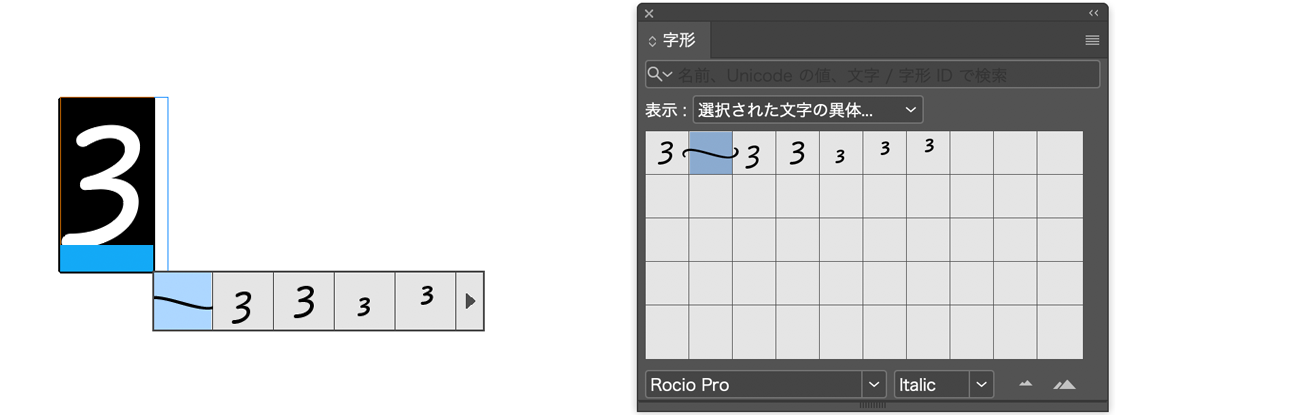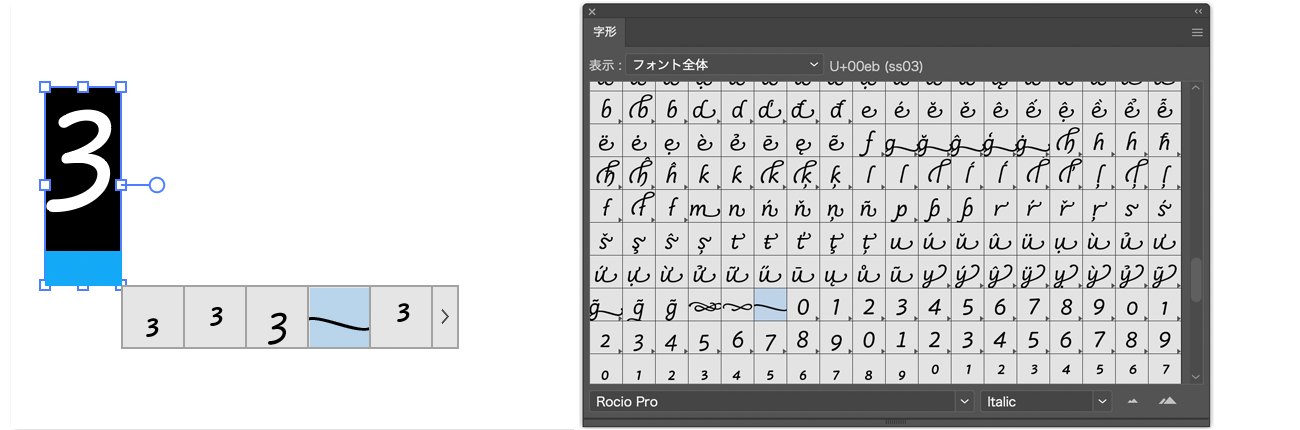
【Rocio Proの特徴】
Rocio ProはRocio(フォントメニュー名:MO Rocio Regular / MO Rocio Italic)を元に文字セットの拡張、ファミリー化、スワッシュ字形へのアクセスの改善をおこなったフォントファミリーです。
各ウエイトのイタリックには装飾的なスワッシュ字形なども多数用意されており、OpenType機能を用いることでテキストの並びに応じた華やかな字形を呼び出して表情豊かなデザインを作り上げることができます。
【Rocio ProとRocioの違い】
Rocio ProはRocioを元に文字セットの拡張とファミリー化を行っているため、スタイル展開や搭載しているグリフの種類が大きく異なります。
ファミリー化に伴いRegularおよびItalicのデザインを調整したため、RocioとRocio Proではデザインも細部で異なります。
また、Rocioでは文脈を判断してスワッシュ字形を呼び出すことがInDesignでのみ可能だった一方、Rocio ProではAdobe Illustratorでも同様のことが可能となりました。
なお、RocioとRocio Proでは文脈を判断してのスワッシュ字形の呼び出しパターンが異なるため、同様の文字列でも必ずしも同様の字形が呼び出されるわけではありません。
このように、デザイン、文字セット、スタイル展開、OpenType機能と多くの面でRocioとRocio Proは異なり、互換性がありません。
そのため、両者間での置き換えを行う場合は組版の崩れにご注意ください。
【Rocio Proの機能と使い方について】
Rocio Proは以下のような機能を備えています。
(1)スワッシュ字形
グリフの並びに応じてスワッシュ字形を呼び出します。文脈を考慮して自動で適切な形を呼び出すことができます。文脈に関係なく特定のデザインを適用したい場合はスタイルセットをご参照ください。
スワッシュ字形(自動)
(2)スタイルセット
スタイルセットメニューから各種スタイルの字形を呼び出します。
スタイルセット機能はフォントごとに設定された代替字形のグループを呼び出す機能です。Rocio Proにおいては、文脈に関係なく選択したテキスト範囲の対象文字全てを特定のデザインに変更します。
Curvy Alternates
カーブしたデザインの字形を呼び出します。
下記3.デザインのバリエーションも参照ください。
Curvy Alternates
Initial Form, Final Form
Initial Formは語頭用、Final Formは語末用のスワッシュ字形を呼び出します。
Initial Form
Final Form
Curvy Ascender/Descender Extension
カーブしたアセンダとディセンダを持つデザインの字形を呼び出します。
Curvy Ascender/Descender Extension
Alternates with Swirls
うずを巻くようなストロークを持った字形を呼び出します。
Alternates with Swirls
Lowercase h with Extended Tail
長いテイルを持った字形のhを呼び出します。
Lowercase h with Extended Tail
(3)デザインのバリエーション
Curvy Alternates
カーブしたデザインの字形を呼び出します。本機能はスタイルセットのCurvy Alternatesと同じ役割を果たします。
(4)オーナメント
プロポーショナル数字1, 2, 3からの置き換えで各種オーナメント(装飾用のグリフ)を呼び出します。
オーナメント